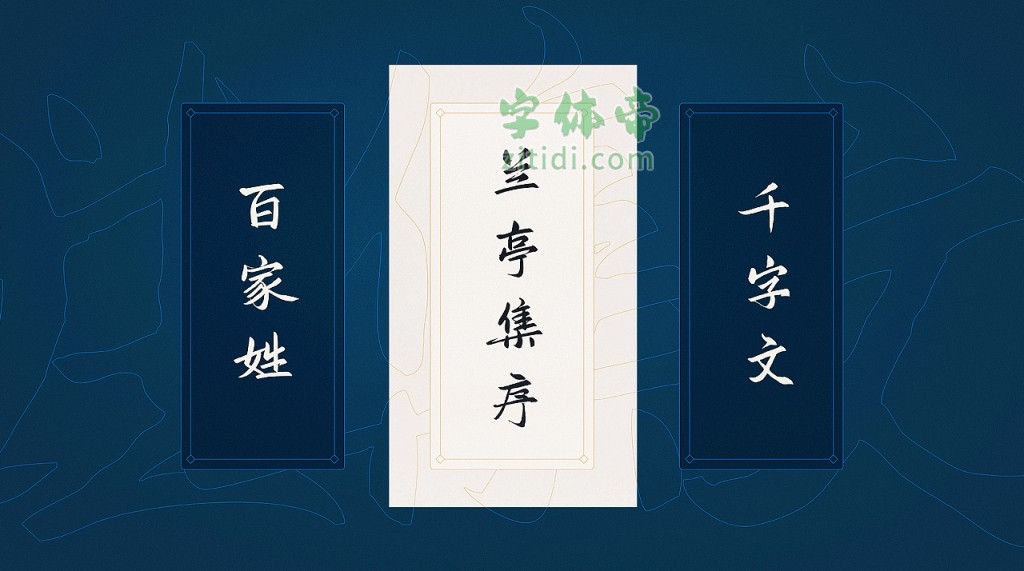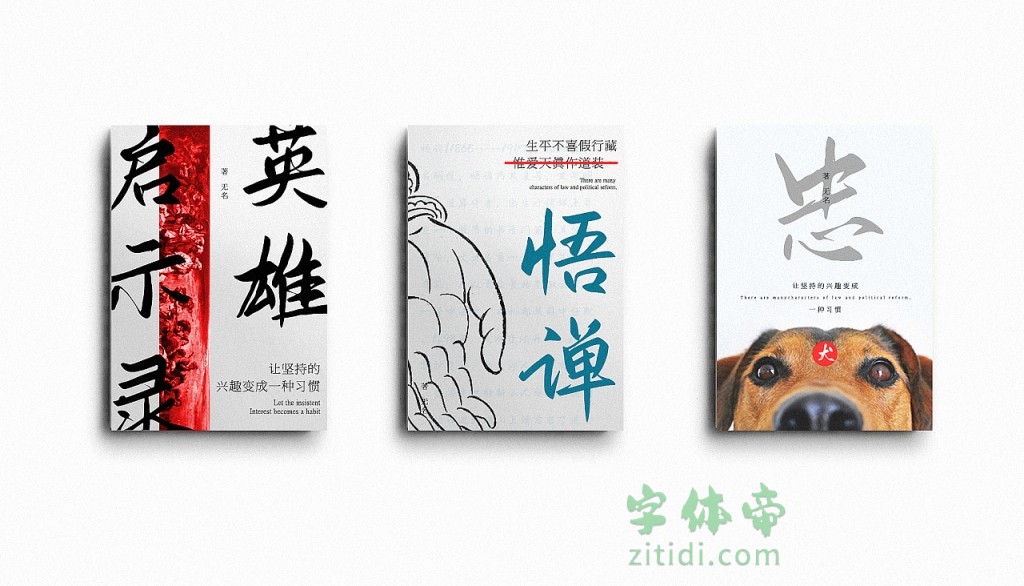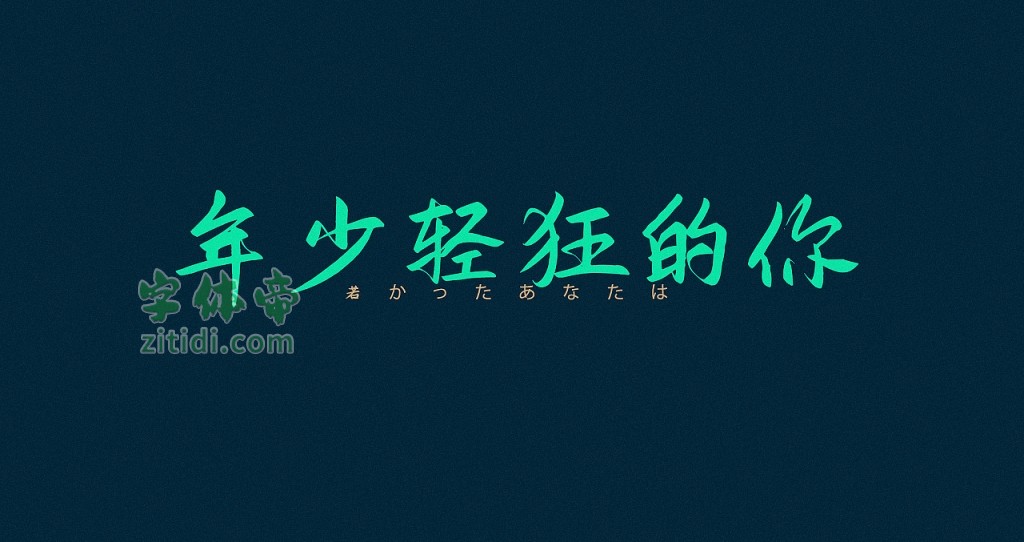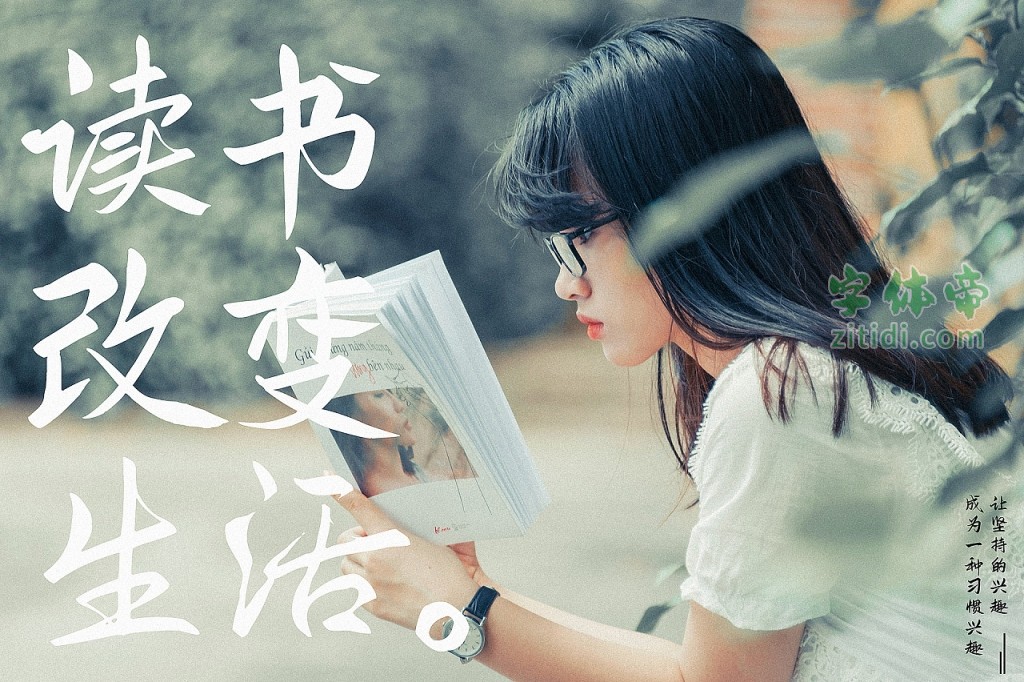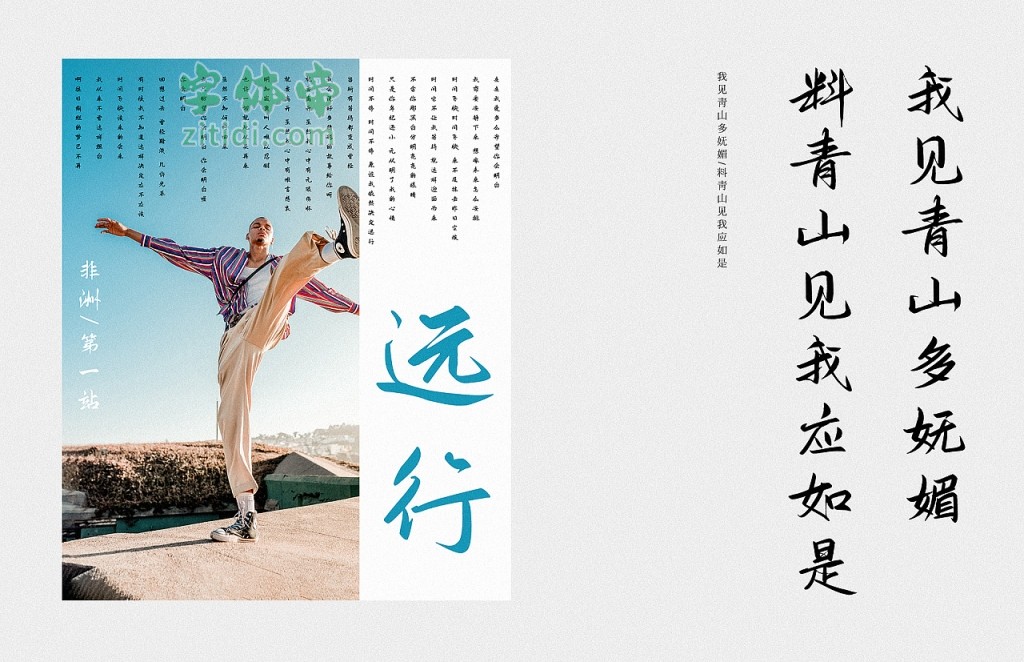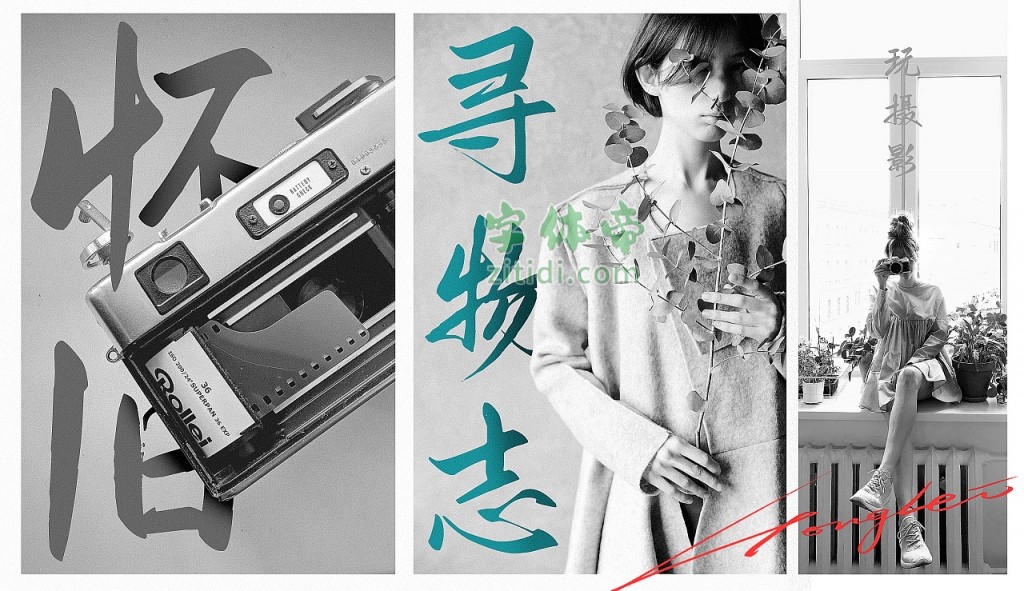
鸿雷板书简体是一款非常漂亮的手写字体,首发于站酷《 啄字丨鸿雷板书字体A(简) 》,免费可商用!
大神这样说:
关于如何看待这个字体我是这么想的“作为一个手写爱好者,我没有经过传统书法的熏陶与练习,走上了江湖道路,凭借满腔喜爱坚持写下这套字体。或许……这套糟糕的字体会拉低了行业字库的水准,但不管好坏也算是圆了我的字库梦想。”
1、如果要问起为什么要写这个套字体?
最初源于练字……当时没有什么可以写的内容,于是想到了抄写千字文。再后来,嗯,都写了1000字了,也不差剩下的五六千字了。于是就有了《鸿雷板书简体》。
2、为什么叫板书简体呢?
因为他是用手绘板写的简体部分
3、如果问到我将如何看待或者如何处置这个《鸿雷板书简体》?
“鸿雷板书简体”是一款书写很新颖的字体,字体大方,适合各种设计作品使用!欢迎下载!